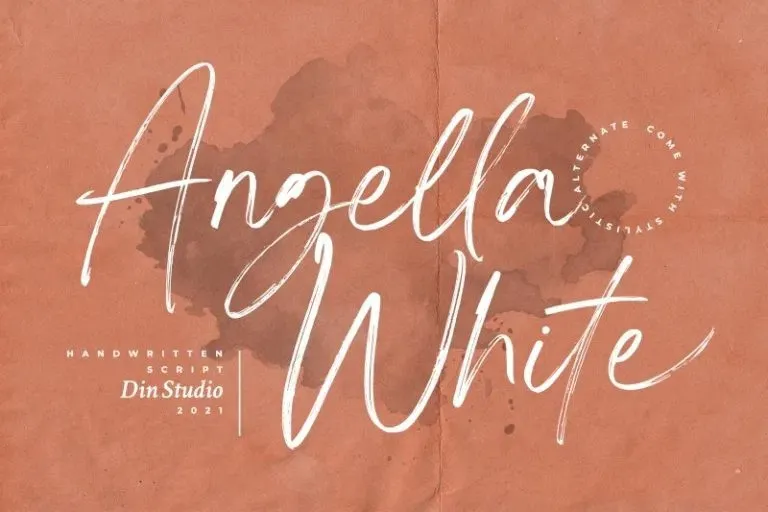
Angella White Font – Download Grátis
A fonte ‘Angella White’ oferece um estilo elegante e moderno que se encaixa perfeitamente para designers interessados em criar projetos únicos. Esta fonte é uma escolha ideal para quem busca algo mais casual, mas ainda sofisticado. Com suas curvas e traços cuidadosamente feitos para entregar alegria e elegância, essa opção de script é perfeita para destacar cabeçalhos em projetos digitais ou impressos. Uma das características distintivas da ‘Angella White’ é seu estilo manuscrito moderno. Composta com um toque de arte, esse design inovador é perfeito tanto para criar destaque nas aparições mais visíveis quanto para personalizar materiais impressos como business cards e convites. Além disso, é uma opção ideal para promover suas vendas online, Instagram quotes e até mesmo textos em camisetas, tudo isso com um toque de elegância que eleva seu trabalho. Designada por Din Studio, a fonte ‘Angella White’ não apenas cumpre as expectativas do designer 99designs, mas também traz uma sensação única para qualquer projeto. É uma maneira perfeita de tornar seus materiais mais chamativos e sofisticados, garantindo que sua mensagem seja percebida em todas as ocasiões onde a ‘Angella White’ é usada.